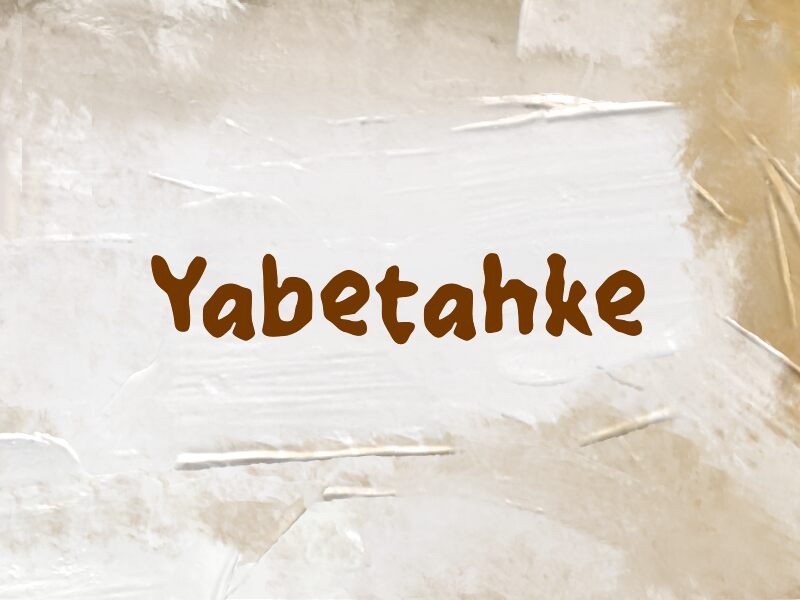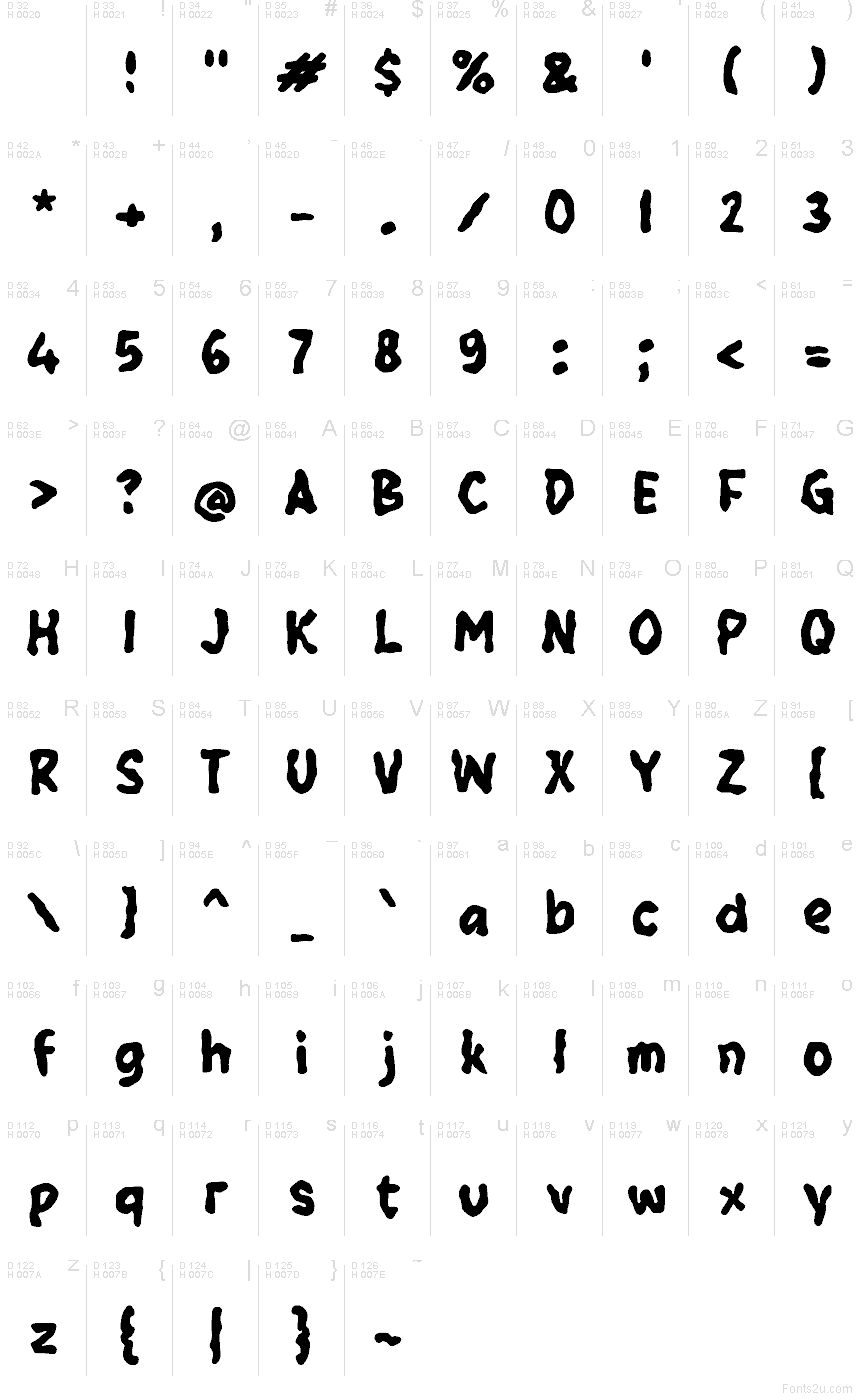
Yabetahke
Yabetahke di Wep è un font display gratuito e distorto, dal look morbido, gonfio e disegnato a mano. Le lettere hanno un aspetto gommoso e anticonformista, con forme spesse e arrotondate, un equilibrio irregolare e curve giocose che rendono la scritta come se fosse inchiostro spalmato, pur mantenendo una solida coerenza visiva.
Questo font gratuito è perfetto per poster, artwork per musica indie, copertine di fanzine, grafiche streetwear e titoli dove il ritmo sciolto e irregolare può dettare l'intera atmosfera. Funziona bene anche per brevi titoli o loghi che richiedono una silhouette grezza, quasi da creatura, piuttosto che un aspetto geometrico troppo ordinato.